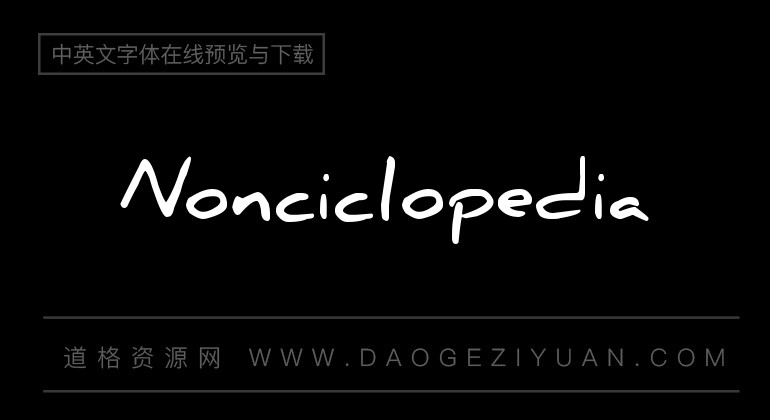
Nonciclopedia 是一款开源的字体,由著名的设计师 Alejandro Paul 创作,该字体以自由的抽象风格为特色,拥有简洁的线条,以及灵活的曲线,它具有较强的灵活性,可以支持多种语言,并且在任何尺寸上都能保持清晰的效果。Nonciclopedia 字体拥有精致的字形设计,能够支持多种文字样式,比如斜体,粗体,着重号等。此外,它还支持多种字体技术,可以提供更好的可读性和可视性。内容介绍
Nonciclopedia是一款非常不错的手写艺术字体,具有很好的视觉感,适合于文化类的宣传设计、商业类品牌的广告和产品包装设计以及个性化文字排版等较多场景。